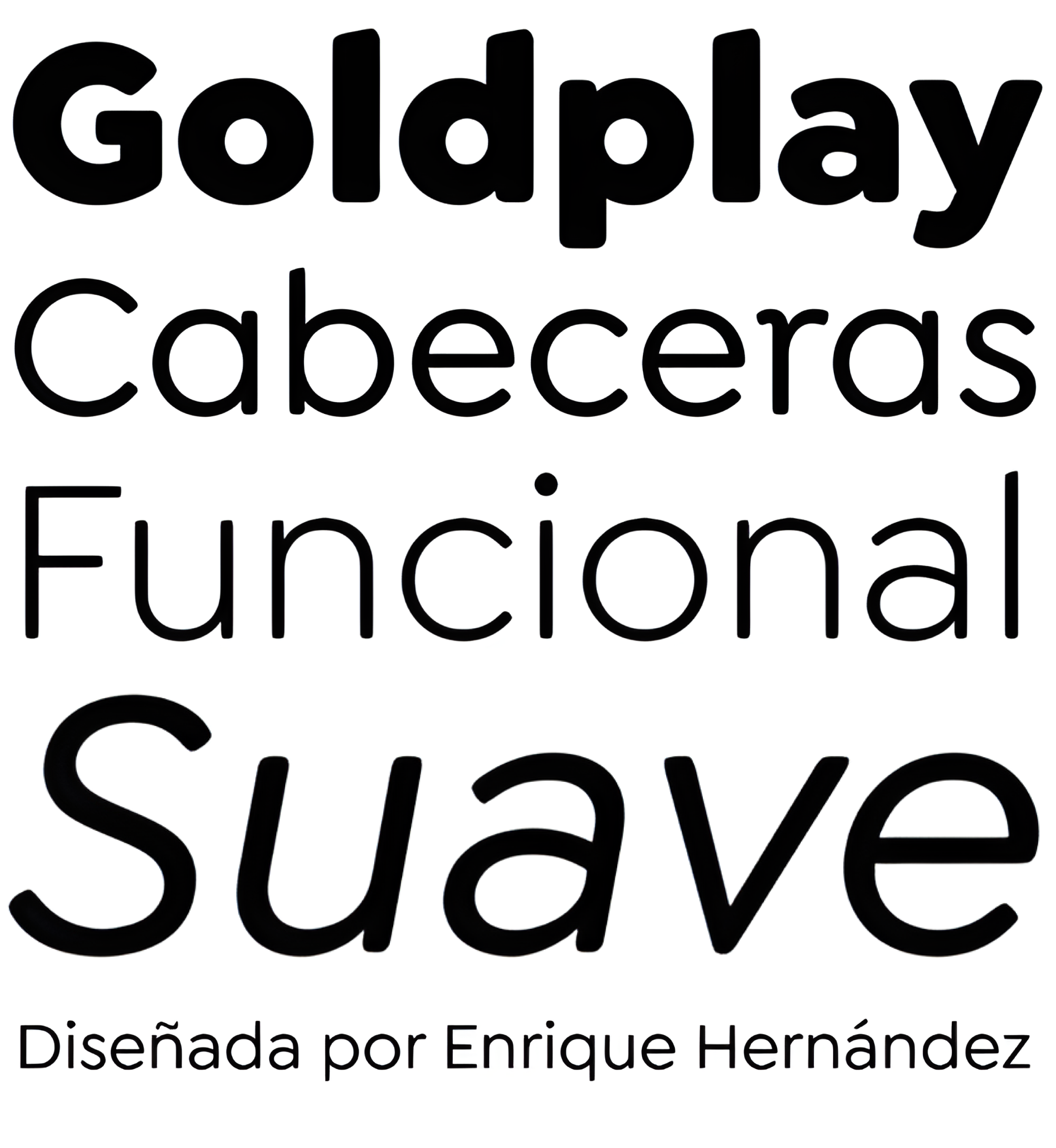
| Año | 2019 |
| Créditos | Enrique Hernández |
| Descripción | Goldplay se basa en Isidora Sans con formas redondeadas. Sus terminales redondeados y suaves le confieren un aspecto amable y expresivo, y su estilo moderno y contemporáneo, así como sus proporciones clásicas, lo convierten en una excelente elección para titulares, logotipos, marcas, libros, revistas, motion graphics y su uso en web y Tv. Una de sus principales características es su gran altura x, que le confiere un aspecto elegante y con clase. Goldplay está disponible en 2 versiones, cada una con 7 pesos, de fino a negro, y cursivas a juego, lo que da un total de 28 fuentes. La versión estándar sin gracias -fresca, limpia y contemporánea- es una opción perfecta para el diseño editorial y corporativo, titulares, libros, revistas o cualquier otra pieza de diseño gráfico. La versión de pantalla Alt semiserif -más expresiva y moderna- es ideal para logotipos, marcas, envases y su uso en web y televisión. Goldplay contiene un conjunto de 540 caracteres compatibles con más de 200 lenguas de base latina. |
| Familia(s) | Goldplay |